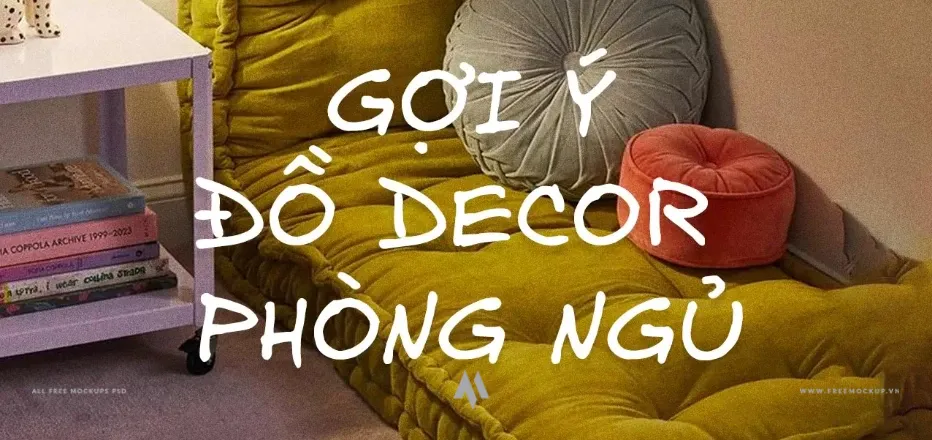
Font DFVN Excalifont Việt hóa
DFVN Excalifont Việt Hóa là bộ font chữ viết tay kỹ thuật số độc đáo, được nâng cấp và kế thừa từ font chữ gốc Virgil của công cụ vẽ sơ đồ nổi tiếng Excalidraw. Với mục tiêu tối ưu hóa trải nghiệm thị giác, Excalifont giữ trọn vẹn nét phác thảo tự nhiên, mộc mạc đặc trưng nhưng cải thiện vượt bậc về độ rõ ràng, giúp văn bản sắc nét và cực kỳ dễ đọc ngay cả trong các sơ đồ hay bản vẽ chi tiết phức tạp.
Đặc điểm nổi bật
• Phong cách phác thảo (Hand-drawn) trực quan: Tái hiện chân thực nét chữ viết tay tự do, mang lại cảm giác gần gũi, phóng khoáng và kích thích tư duy sáng tạo.
• Tối ưu khả năng đọc (Legibility): Cấu trúc ký tự được tinh chỉnh gọn gàng, khoảng cách chữ thoáng đãng, khắc phục hoàn toàn nhược điểm khó nhìn của các font viết tay thông thường.
• Chuẩn hóa tiếng Việt đầy đủ: Bộ dấu tiếng Việt được trau chuốt đồng bộ với phong cách vẽ tay, hiển thị mượt mà trên Figma, Adobe Photoshop, Illustrator, Canva và các công cụ ghi chú số.